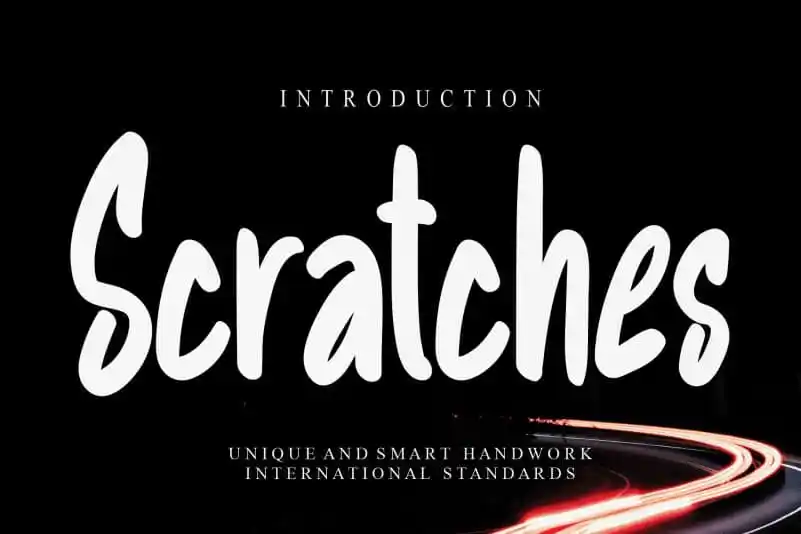
A fonte ‘Scratches Display Font’ é uma escolha elegante para designers que buscam uma fonte visualmente atraente e versátil para criar mensagens impactantes, desde embalagens de produtos até materiais de marketing impressos. Com sua tipografia forte e vibrante, essa fonte captura atenção imediatamente, ideal para marcas criativos e ambientes onde queremos destacar o design. A criação ‘CreativeLetter’ trouxe consigo uma experiência única e detalhada desta fonte. As linhas finas e os espaçamentos cuidadosos em cada caractere garantem um acabamento que transmite confiabilidade, enquanto a disposição dos traços fornece uma textura que chama à atenção. Suas formas redondas e suaves combinam perfeitamente com texturas geométricas para criar um contraste harmonioso. ‘Scratches Display Font’ é o ideal para designers que querem incorporar elementos de design visualmente atraentes em seus projetos, seja para um site profissional ou uma campanha publicitária. Com a capacidade de transformar qualquer projeto em um design poderoso e memorável, essa fonte é como se você pudesse dar vida à sua marca através do seu próprio estilo único.